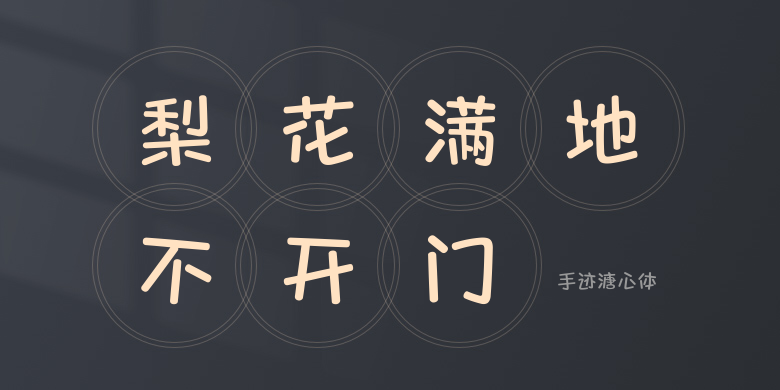
手迹溏心体
手迹溏心体,这款字体结构工整、笔画清晰,兼顾美观与易读性,适用于标题、正文、海报、包装、LOGO 等多种场景。字形优雅稳定,风格百搭耐看,适配日常排版与创意设计,让文字呈现更舒适、更具质感。手迹溏心体一笔一画,皆是细节,以均衡的比例、流畅的线条打造舒适视觉体验,字形端正大气,风格简约现代。无论是商业设计、品牌宣传还是日常排版,都能轻松驾驭,让文字更有格调与力量。手迹溏心体字体下载。